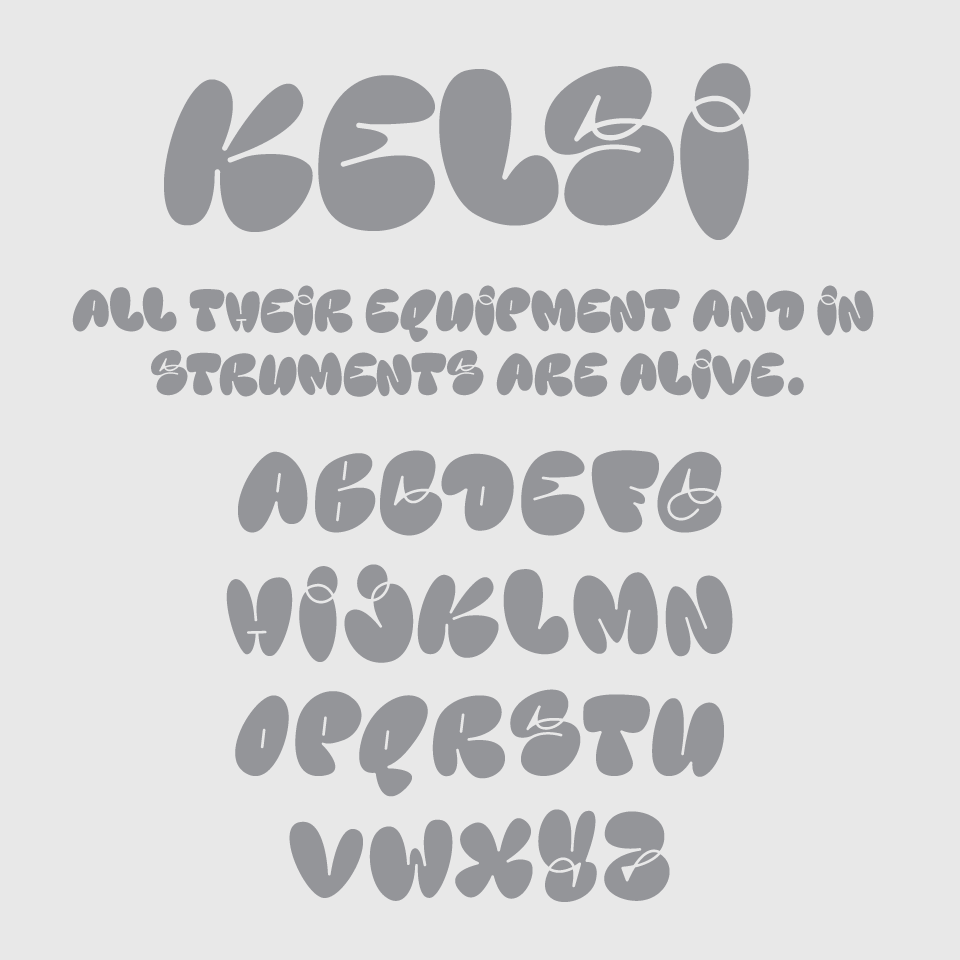
Kelsiフォントは、ぷっくりとした文字のかたちが特徴的な、手書き文字のような元気でおおらかな雰囲気をもつフォントです。どの文字もまるで風船のようにふくらんでいて、思わず笑顔になるような愛嬌があるフォントです。
文字の中にまじったゆるやかなラインがアクセントになっていて、子ども向けのグラフィックや、ポップでやさしい印象にしたい場面で活躍する、遊び心たっぷりのフォントです。
収録文字は、大文字の収録となっています。